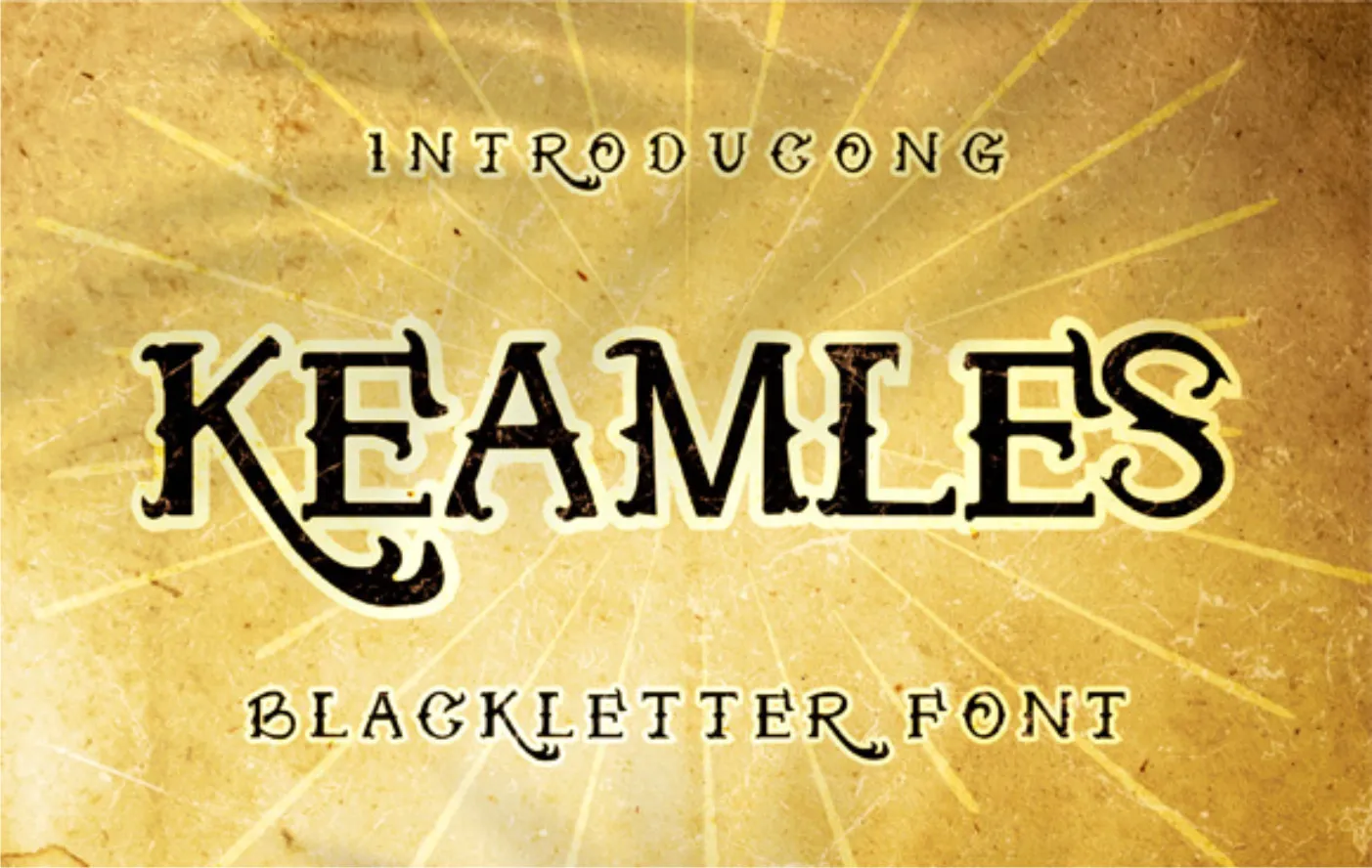
Keamles Font – Download Grátis
Esta é uma fonte Blackletter chamada Keamles Font, projetada por letterfiastudio. O que torna essa fonte única são suas linhas finas e desenhadas com precisão, criando um efeito elegante que complementa qualquer tipo de design gráfico. Seja você criando um layout para uma revista histórica ou trabalhando em uma capa de livro antigo, Keamles tem o poder de transformar seus projetos em algo singularmente impressionante. Com seu estilo arcaico e sofisticado, essa fonte se destaca como uma mão na obra indispensável para qualquer biblioteca de fontes. Seja você um designer ou editor de textos, Keamles Font certamente merece uma vaga entre suas ferramentas favoritas.